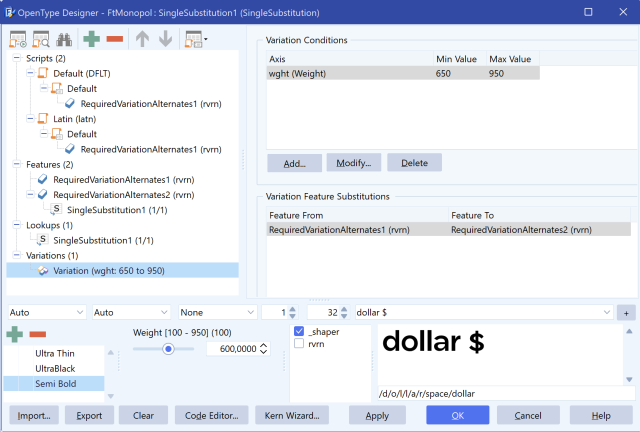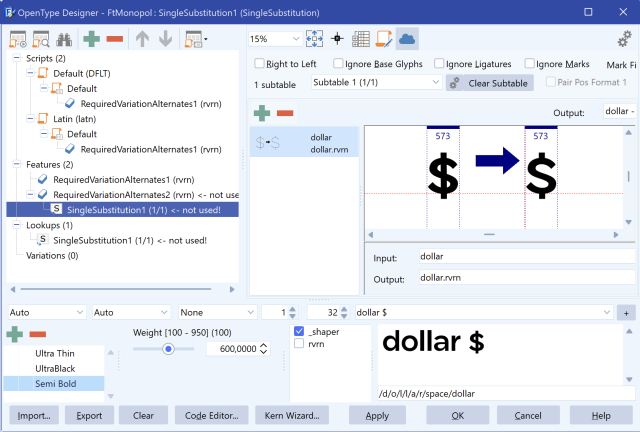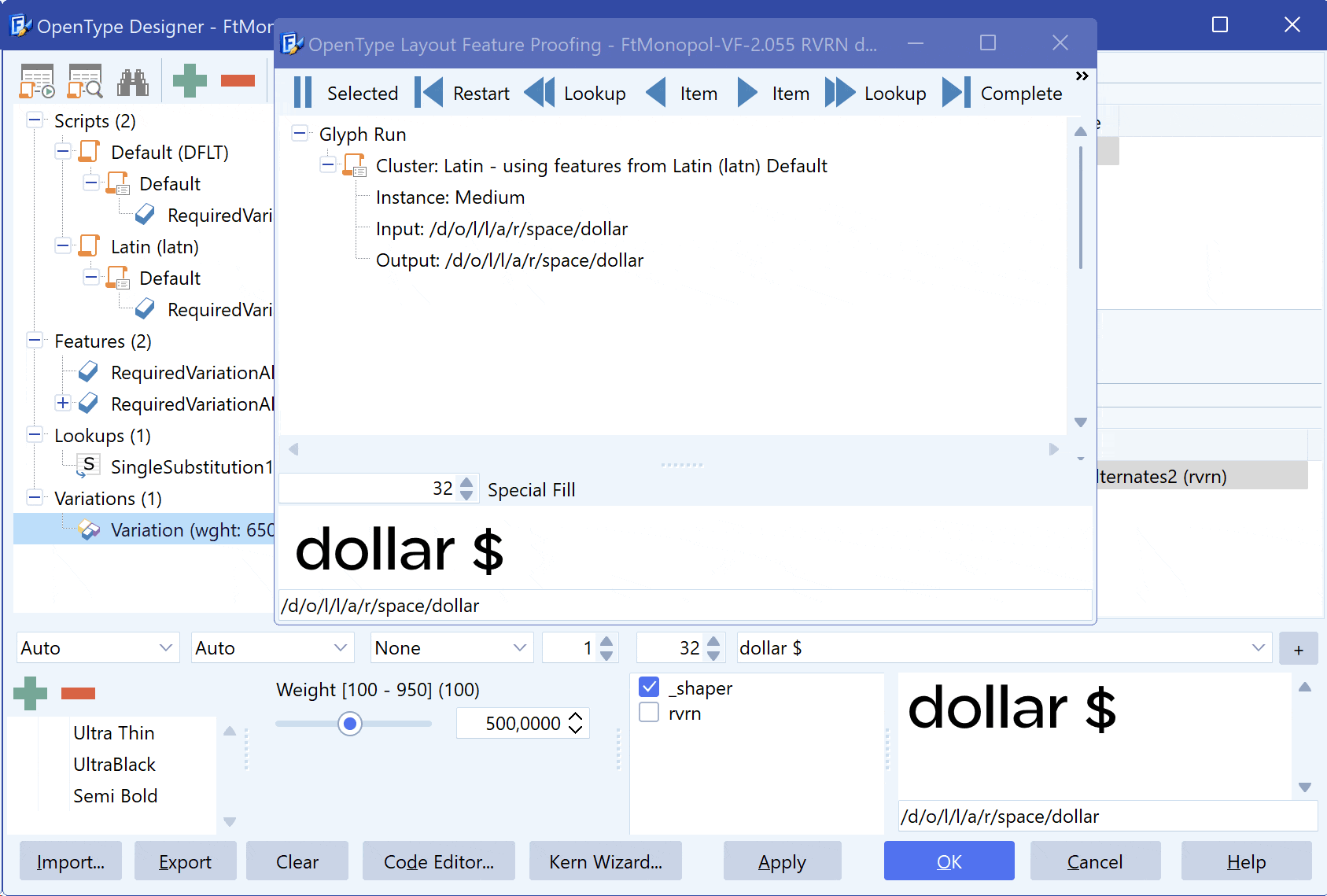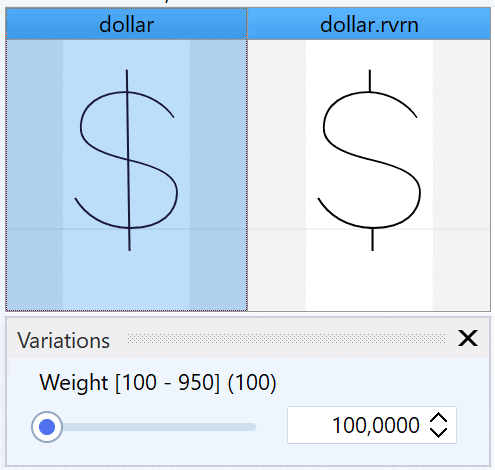
使用特性變化 切換字形
本教程演示如何根據可變字型的變化例項(這裡是 Weight 字重軸),將單豎線的美元符號切換為帶斷條的備選設計。
簡介
可變字型允許您使用軸滑塊插值字形層輪廓。這是可能的,因為所有層都具有相容的輪廓,這意味著它們具有相同數量的輪廓和匹配的點,僅在點座標上有所不同。然而,如果您需要在設計空間內的特定範圍內切換到不相容的輪廓怎麼辦?例如,您可能希望為更窄或更粗的字形使用不同的字形設計。
問題
想象一個場景,您希望帶有單豎線的美元符號切換到帶有斷槓的替代設計,適用於更粗的字重(例如,當字重軸為 650 或更高時)。這就是 OpenType 的特性變化發揮作用的地方。
美元符號變化
解決方案:OpenType 特性變化
OpenType 規範透過特性變化表提供了一個優雅的解決方案,允許您將包含預設查詢集的特性替換為包含需要在特定條件下應用的查詢的替代特性。
有一個專門用於此的功能稱為必需變化替代(rvrn)。根據規範,rvrn 功能中的所有查詢必須是單一替換(GSUB 型別 1),這意味著不允許使用連字、上下文或 GPOS 查詢。然而,某些應用程式並未完全按照 OpenType 規範的意圖支援 rvrn,這可能會導致問題。
如果您使用 rvrn 的特性變化不起作用,您可以自由使用其他功能。我們建議嘗試必需連字(rlig)作為替代。此功能沒有與 rvrn 相同的限制,允許使用連字查詢。
在 FontCreator 中新增特性變化的分步指南
1. OpenType 設計器
• 啟動 FontCreator。
• 確保您的字型具有美元字形以及替代的 dollar.rvrn 字形。
• 開啟 OpenType 設計器。
2. 建立新查詢
• 在左側的功能樹檢視中選擇名為"查詢"的根項。
• 單擊新增按鈕(頂部的綠色十字)。
• 從右側的 GSUB 列表中選擇"單一替換"。
• 將此查詢命名為"SingleSubstitution1"並將其配置為用替代字形替換常規美元符號。
3. 向 OpenType 佈局新增功能
• 如果您的字型沒有指令碼,則首先選擇"指令碼"並單擊新增按鈕以新增"預設" -> "預設",否則您可以跳過此步驟。
• 選擇名為"功能"的根項以新增名為"RequiredVariationAlternates1"的 `rvrn` 功能(將其留空,不新增查詢)。
• 現在將該功能新增到所有可用的指令碼-語言組合。
• 我們向"功能"新增第二個 `rvrn` 功能並將其命名為"RequiredVariationAlternates2"。
• 將查詢"SingleSubstitution1"新增到"RequiredVariationAlternates2"。
OpenType 設計器
4. 將功能與變化條件連線
• 在功能樹檢視中,選擇"變化"(最後一個根項)並單擊新增按鈕(頂部的綠色十字)。
• 在變化條件部分,單擊新增按鈕並將軸設定為"字重",最小值設定為 650,最大值設定為 950。
• 新增變化功能替換,將"RequiredVariationAlternates1"設定為功能來源,將"RequiredVariationAlternates2"設定為目標功能。
變化條件
這是完整的功能程式碼:
languagesystem DFLT dflt;
languagesystem latn dflt; # Latin default
lookup SingleSubstitution1 { # GSUB lookup type SingleSubstitution
sub dollar by dollar.rvrn;
} SingleSubstitution1;
feature rvrn { # Required Variation Alternates
} rvrn;
conditionset ConditionSet1 {
wght 650 950;
} ConditionSet1;
variation rvrn ConditionSet1 { # Required Variation Alternates
lookup SingleSubstitution1;
} rvrn;
測試特性變化:
• 透過在預覽區域中輸入美元符號來測試設定。
• (可選)開啟校對對話方塊(左上角的第二個圖示)以檢視形狀引擎處理的內容。
• 使用字重滑塊檢視當字重為 650 或更高時美元符號是否被替換。
• 透過勾選 _shaper 核取方塊確保形狀引擎處於活動狀態。
測試特性變化
結論
透過此設定,您可以有效地管理字形在可變字型中不同軸位置的變化,確保您的設計在各種樣式和字重下保持最佳狀態。